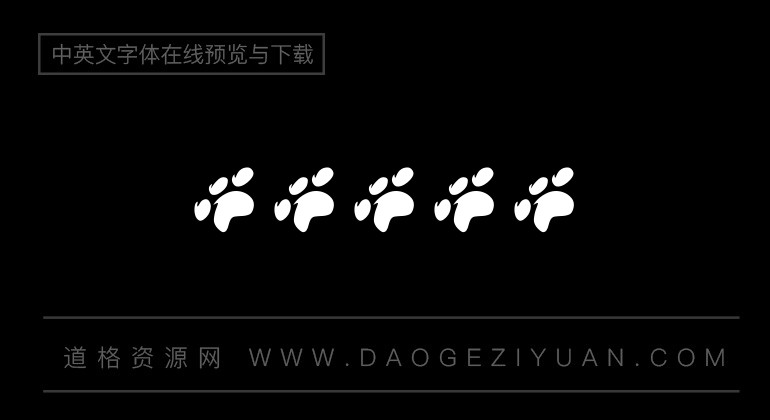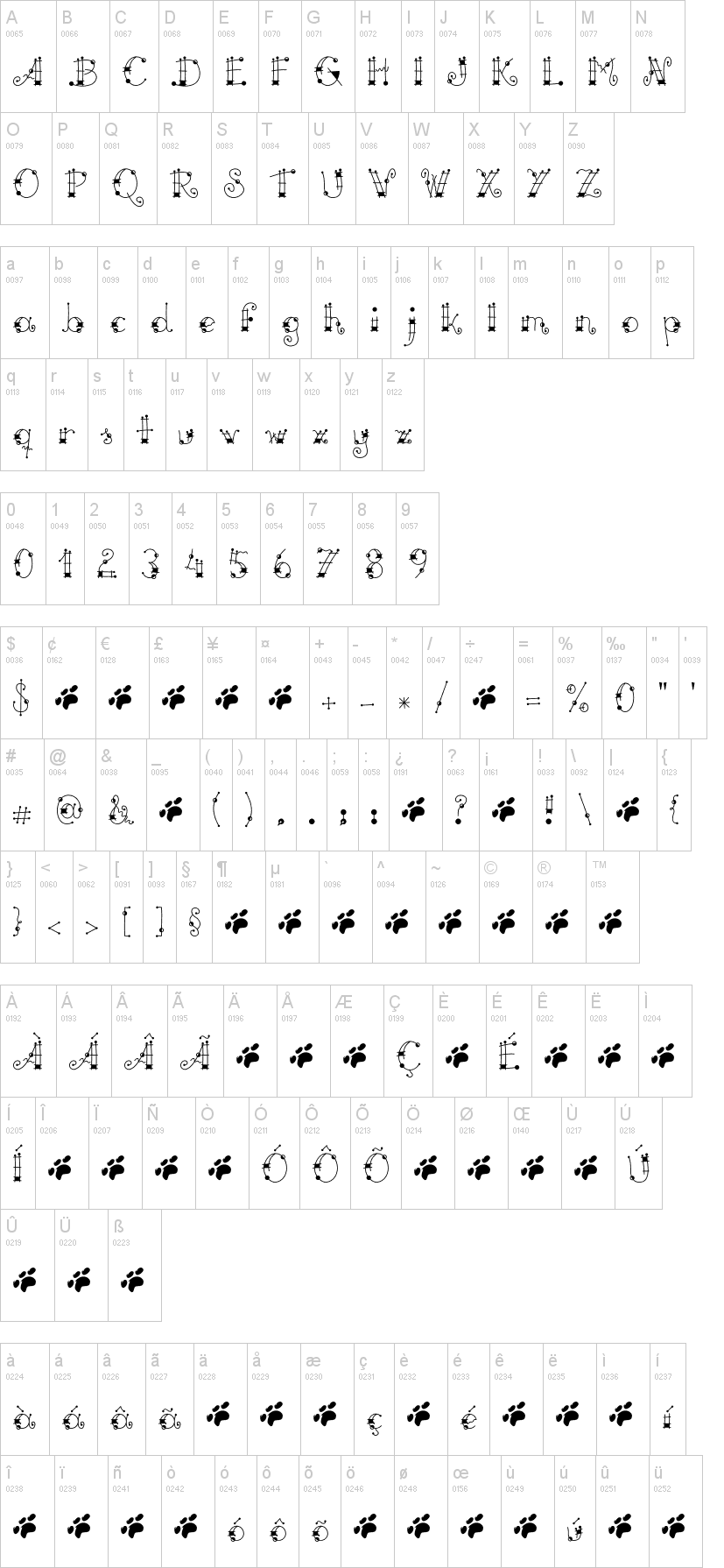
Miroh
? Miroh 字体是一款简约、清新的英文字体,由日本设计师Koji Sano设计。Miroh字体的特点是细节极其精致,线条细腻,字体的曲线柔和,使字体看起来十分清新。Miroh字体支持多种语言,可以用于多种用途,如广告、网页设计、品牌设计等,是一款非常适合用于设计艺术作品的字体。
Miroh是一款非常不错的手写艺术字体,具有很好的视觉感,适合于文化类的宣传设计、商业类品牌的广告和产品包装设计以及个性化文字排版等较多场景。